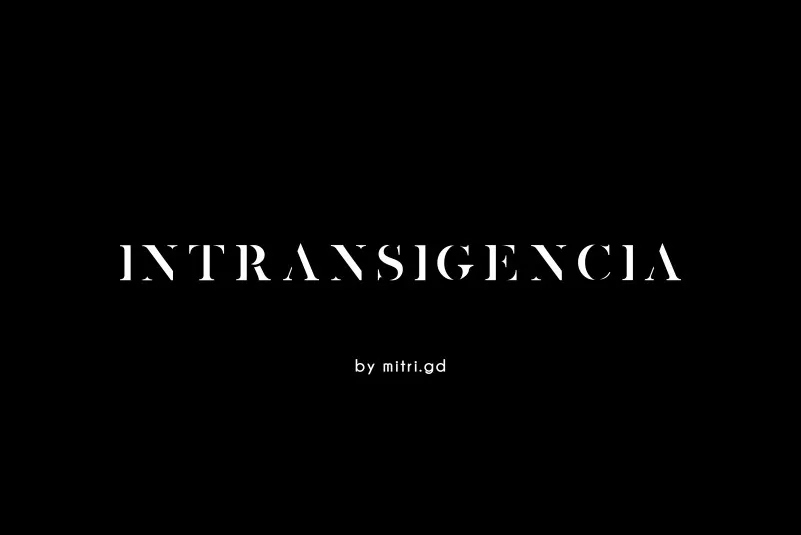
A Intransigencia Serif Font é uma fonte serif que oferece características elegantes para seus projetos escritos. Perfeita para trabalhos inspirados em temas elegantes, essa fonte também se destaca como ideal para aqueles desejando incorporar elementos vintage elegantes. Desenhada e compartilhada pela Mitri Graphic Design, ela é uma escolha ideal para quem busca um toque de sofisticação em suas criações gráficas. Através da Intransigencia Serif Font, você pode introduzir uma dose extra de elegância aos seus projetos, seja para jornais elegantes ou para aqueles trabalhos que exigem um certo clima nostálgico e distinto.